Font chữ quyết định đến 40% ấn tượng đầu tiên của một slide nhưng hầu hết người dùng vẫn dùng Calibri hoặc Arial mặc định. Bài viết này, In Viva sẽ chia sẻ link tải font chữ đẹp PowerPoint và hướng dẫn dùng đúng để slide thuyết trình trông chuyên nghiệp và khác biệt.
| Font | Nhóm | Phù hợp cho |
|---|---|---|
| Be Vietnam Pro | Sans-serif | Mọi loại slide, thương hiệu Việt, doanh nghiệp |
| Montserrat | Sans-serif geometric | Startup, tech, pitch deck đầu tư |
| Lora | Serif | Học thuật, báo cáo nghiên cứu, giáo dục |
| Raleway | Sans-serif elegant | Thiết kế, sáng tạo, portfolio, thời trang |
| Nunito | Sans-serif tròn | Giáo dục, đào tạo, thương hiệu thân thiện |
| Playfair Display | Serif display | Tiêu đề slide ấn tượng, editorial, luxury |
Đặc điểm của các font đẹp cho PowerPoint
Không phải font nào cũng hoạt động tốt trên màn hình thuyết trình. Font chữ PPT đẹp cần đáp ứng đồng thời ba tiêu chí mà font in ấn thông thường không bắt buộc phải có.
- Đọc rõ từ xa: Màn hình thuyết trình thường ở khoảng cách 3–10 mét so với người xem. Font có x-height lớn và nét rõ ràng như Be Vietnam Pro, Montserrat hay Nunito đọc tốt hơn nhiều so với font mảnh hay font có nhiều chi tiết trang trí nhỏ.
- Hiển thị nhất quán trên nhiều màn hình: Font Google Fonts được render tốt trên cả Windows, macOS và màn hình chiếu. Tránh dùng font hệ thống đặc thù (như SF Pro trên Mac) vì sẽ bị thay thế khi mở file trên máy khác.
- Hỗ trợ tiếng Việt Unicode đầy đủ: Font phải có đầy đủ ký tự tiếng Việt để dấu không bị thiếu hoặc hiển thị sai khi mở file trên máy tính khác trong buổi thuyết trình.
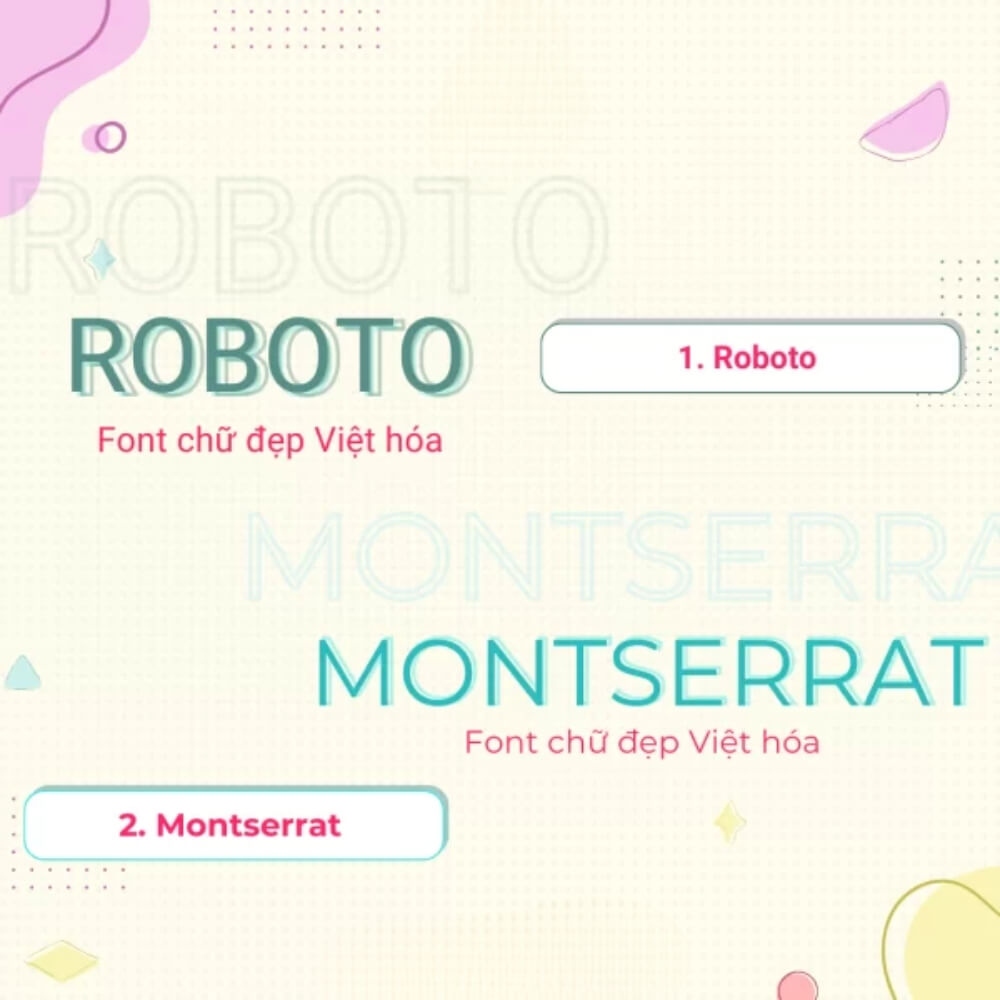
Ứng dụng font đúng cách trong PowerPoint
Chọn được font chữ thuyết trình đẹp chỉ là bước đầu, cách phối và áp dụng font trong slide quyết định thiết kế trông chuyên nghiệp hay nghiệp dư.
- Dùng tối đa 2 font trong một file PPT: một font cho tiêu đề (heading) và một font cho nội dung (body). Ví dụ: Playfair Display Bold cho tiêu đề, Be Vietnam Pro Regular cho body text.
- Cỡ chữ tối thiểu cho từng vùng: tiêu đề slide tối thiểu 28pt, nội dung body tối thiểu 18pt, chú thích tối thiểu 14pt. Nhỏ hơn các ngưỡng này, người ngồi cuối phòng sẽ không đọc được.
- Dùng weight để tạo cấu trúc thay vì dùng nhiều cỡ chữ: thay vì tiêu đề 32pt và nội dung 24pt, thử tiêu đề Bold 28pt và nội dung Regular 18pt — tương phản weight tạo cấu trúc rõ hơn và slide trông gọn hơn.
- Embed font trước khi gửi file: vào File → Options → Save, tích chọn Embed fonts in the file trước khi lưu và gửi file PPT. Bước này đảm bảo font hiển thị đúng khi người nhận mở file dù không có font cài sẵn.
Lỗi thường gặp khi dùng font chữ đẹp PowerPoint
Khi thiết kế slide PowerPoint, bạn nên tránh những lỗi về font dưới đây để đảm bảo nội dung rõ ràng, dễ đọc và chuyên nghiệp hơn.
- Không embed font trước khi gửi file và font bị thay thế khi mở trên máy khác. Đây là lỗi phổ biến nhất thiết kế đẹp trên máy mình nhưng bị vỡ layout hoàn toàn khi thuyết trình trên máy khác. Luôn embed font hoặc export slide thành PDF nếu chỉ cần trình chiếu mà không chỉnh sửa.
- Dùng font script hoặc font trang trí cho body text. Font như Bali Script hay Morva đẹp cho logo nhưng không thể đọc được ở 18pt từ cuối phòng. Body text cần font sans-serif hoặc serif đơn giản, rõ ràng.
- Dùng quá nhiều font và weight khác nhau trong cùng một slide. Mỗi sự thay đổi về font, weight và cỡ chữ là một tín hiệu thị giác quá nhiều tín hiệu khiến người xem không biết đâu là thông tin quan trọng.
- Dùng font màu trắng trên nền sáng hoặc font màu tối trên nền tối. Contrast giữa màu chữ và màu nền tối thiểu phải đạt tỉ lệ 4.5:1 theo chuẩn WCAG để đọc rõ trong mọi điều kiện ánh sáng phòng thuyết trình.
Font nào thay thế được Calibri trong PowerPoint mà vẫn an toàn?
Be Vietnam Pro Regular là lựa chọn tốt nhất thiết kế tương tự Calibri về cảm giác trung tính và dễ đọc nhưng hỗ trợ tiếng Việt tốt hơn và trông hiện đại hơn.
Tại sao slide trông khác khi gửi cho người khác dù đã dùng font phổ biến?
Ngay cả font phổ biến cũng có thể bị thay thế nếu máy người nhận không cài đúng phiên bản. Giải pháp chắc chắn nhất là embed font hoặc export thành PDF trước khi gửi.